今天,跟大家分享字体设计的一些基本设计知识——字体风格的分类。
字体风格是指字体设计中所表现出的综合特点。每一种风格都能使观者产生不同的视觉倾向,这种倾向又能进一步带给人相应的心里联系,使观者通过字体感受到跌宕起伏的情绪波动。
下面带大家一起看看平面设计中常见的字体都有哪些风格。
古典优雅型
该类字体风格往往给人以一种充满浪漫、优雅的视觉印象,展现画面的独特魅力,也能完美地诠释设计目标的实体形象,使观者感到赏心悦目。以印品芷兰体为例:
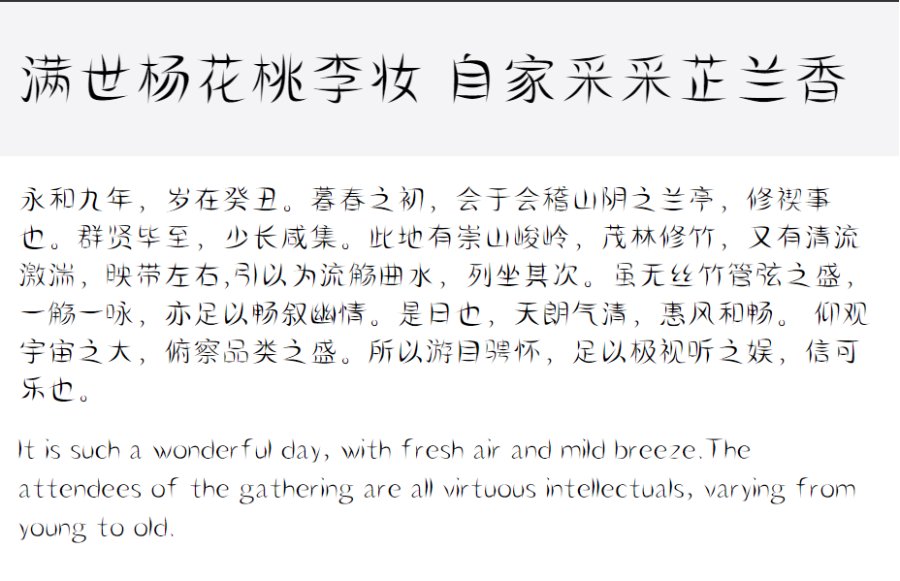
怀旧复古风格
怀旧复古也是一种时尚,它们是过去岁月中美好事物的集合体,对生活在当下的我们来说,它们也是过去时空里的流行思潮,设计者通常结合现代与复古两种元素来对字体风格进行塑造,以此来迎合观者的怀旧情怀。我们可通过汉标铁林篆(繁)来感受下。
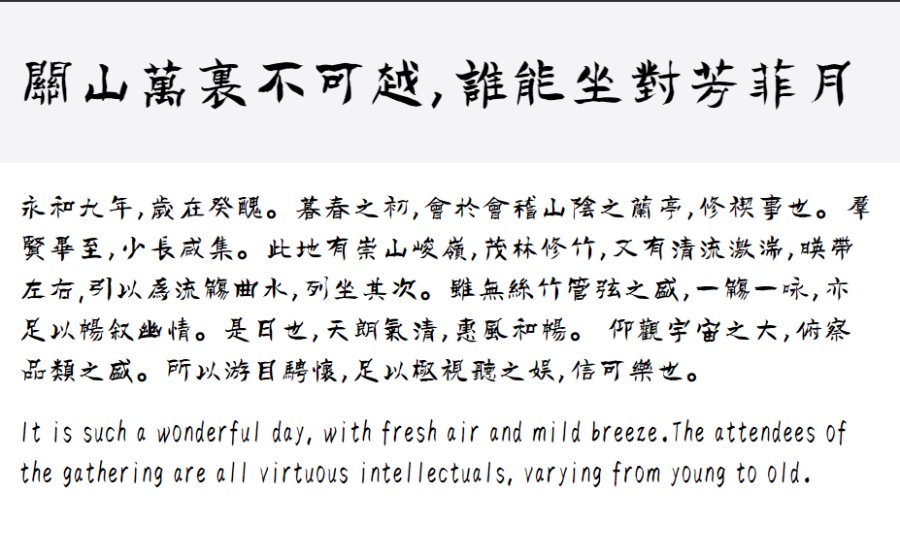
活泼俏皮风
这类风格的字体没有固定的的设计形式,在创作时讲究随性而发,设计者通过笔画的延展来表现随性的活泼感,还可以借助活泼俏皮的字体风格示人感到轻松愉悦。下图是上首玉立体展示图。